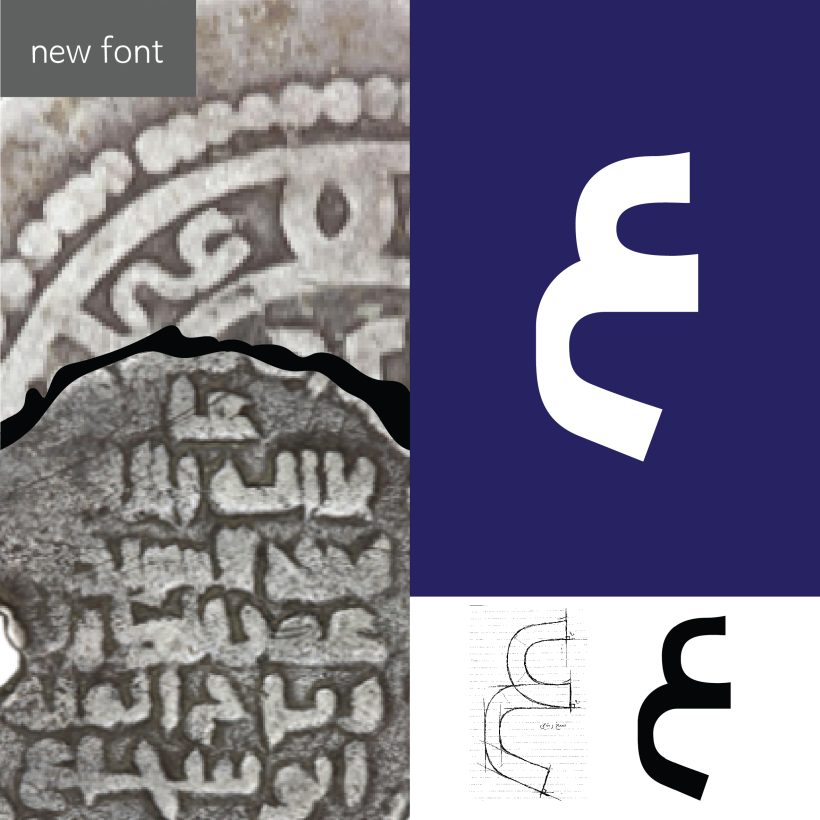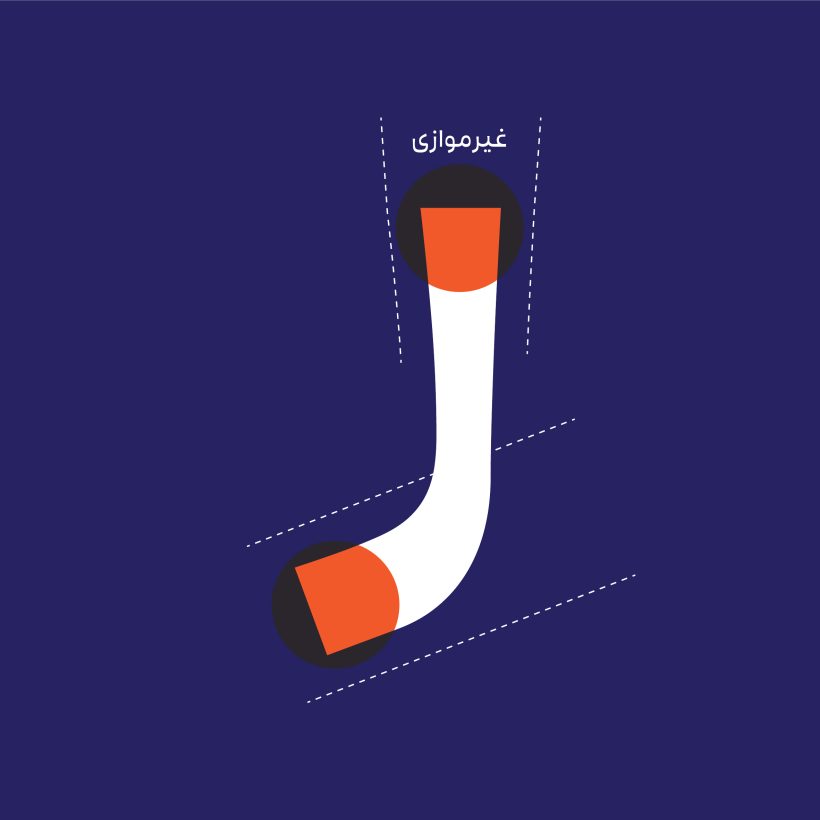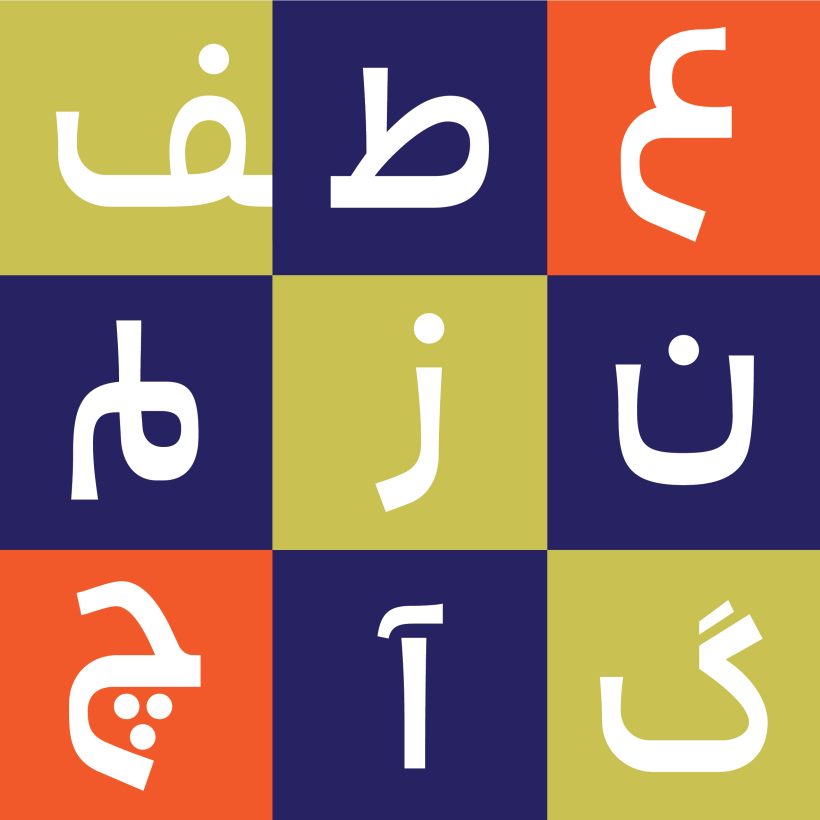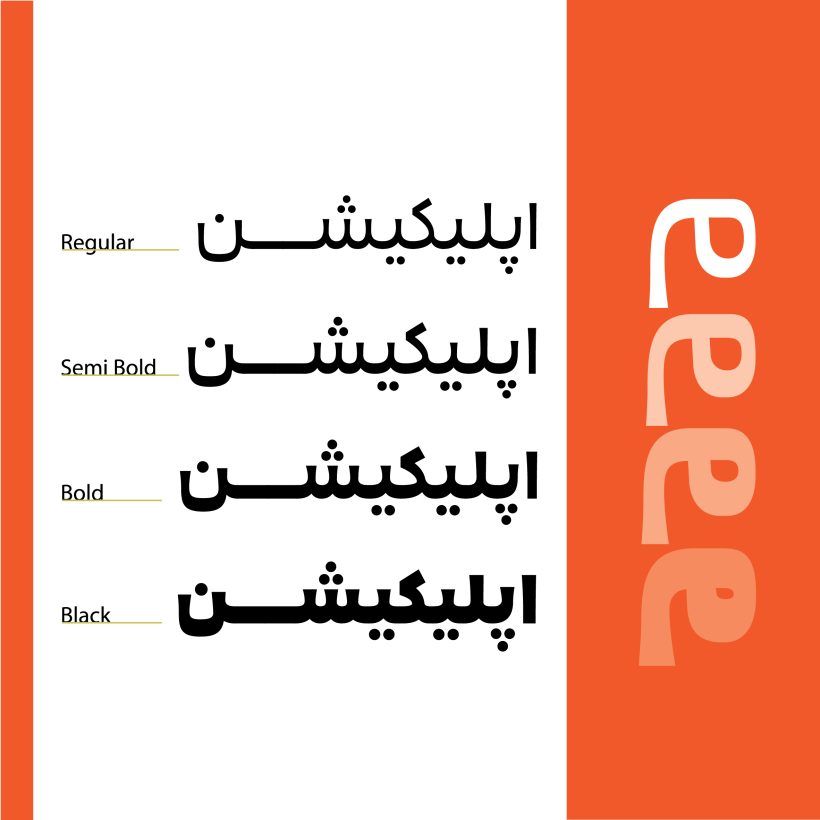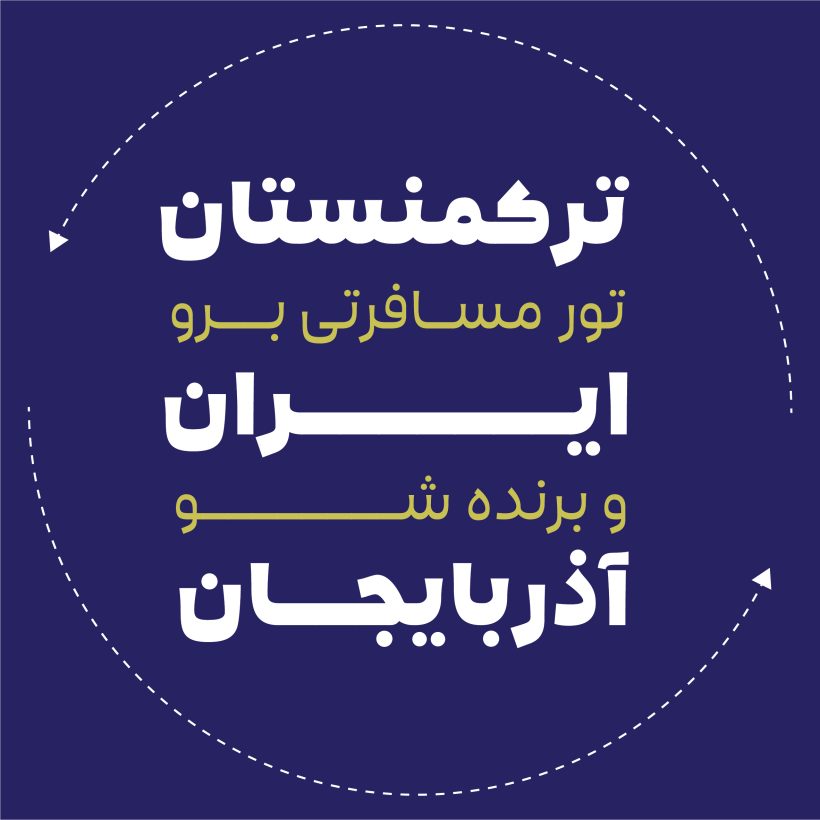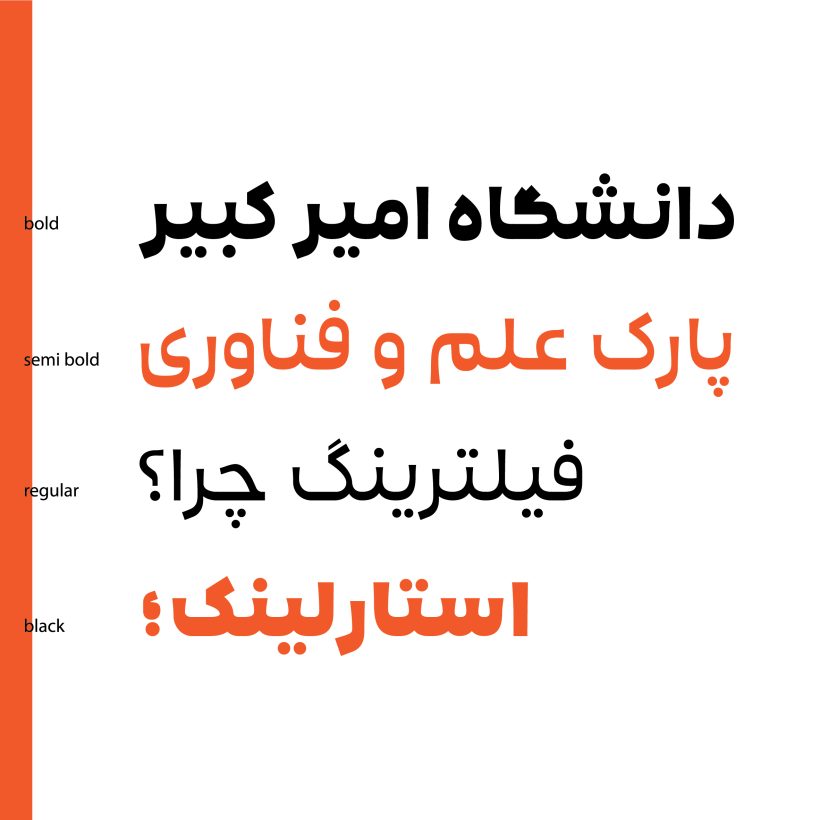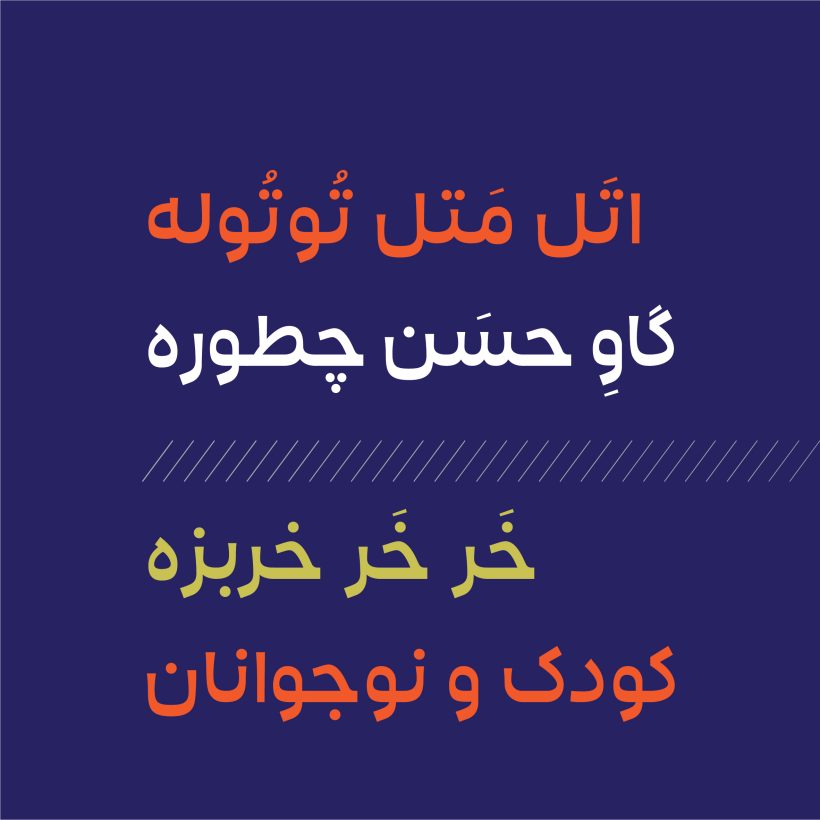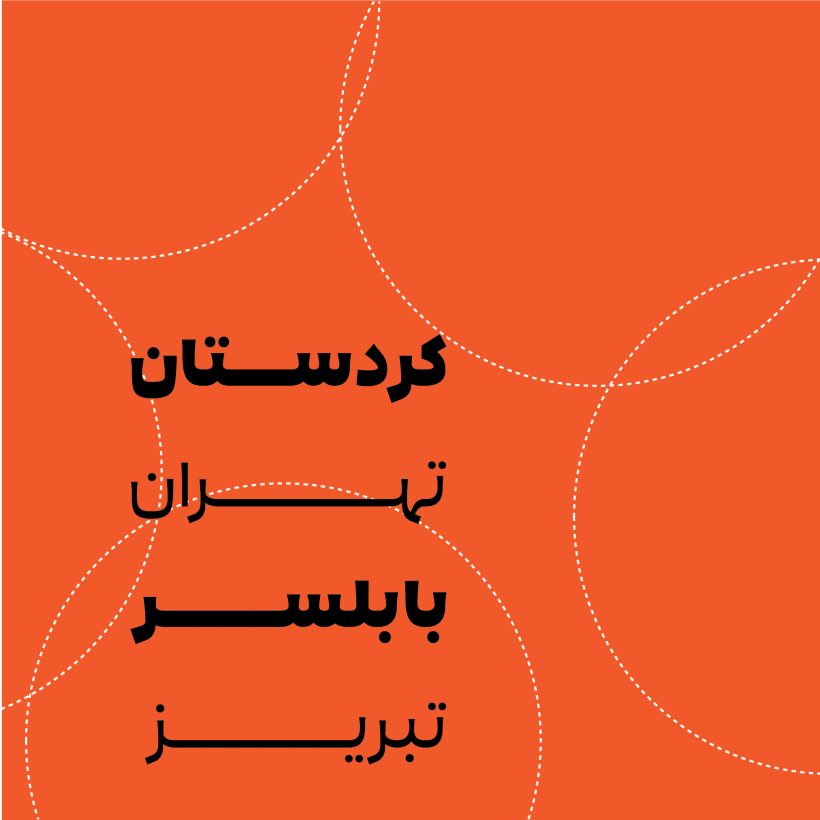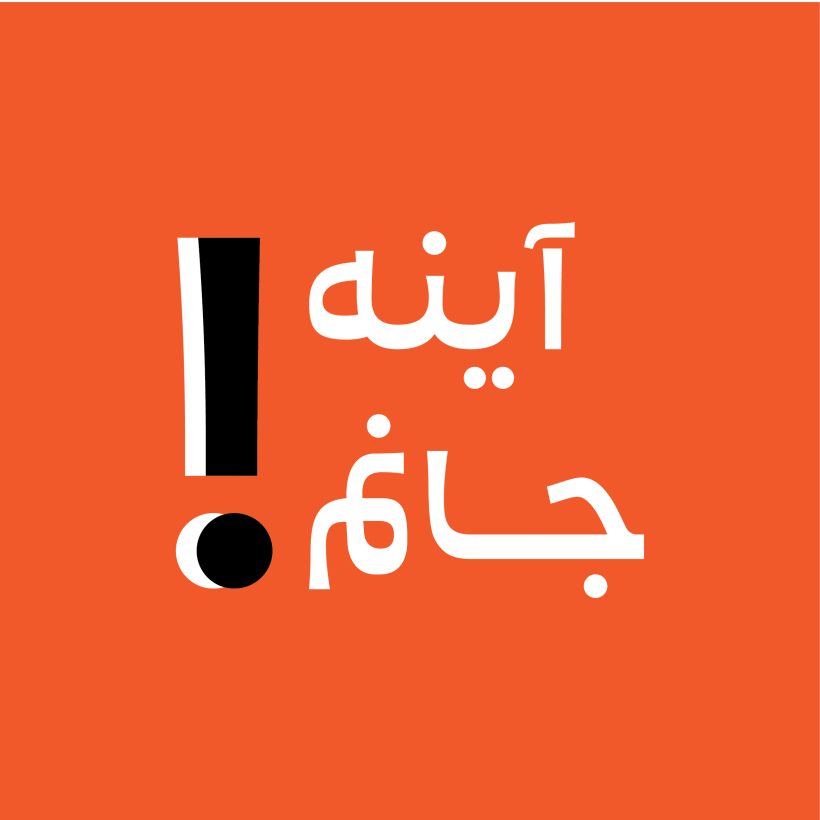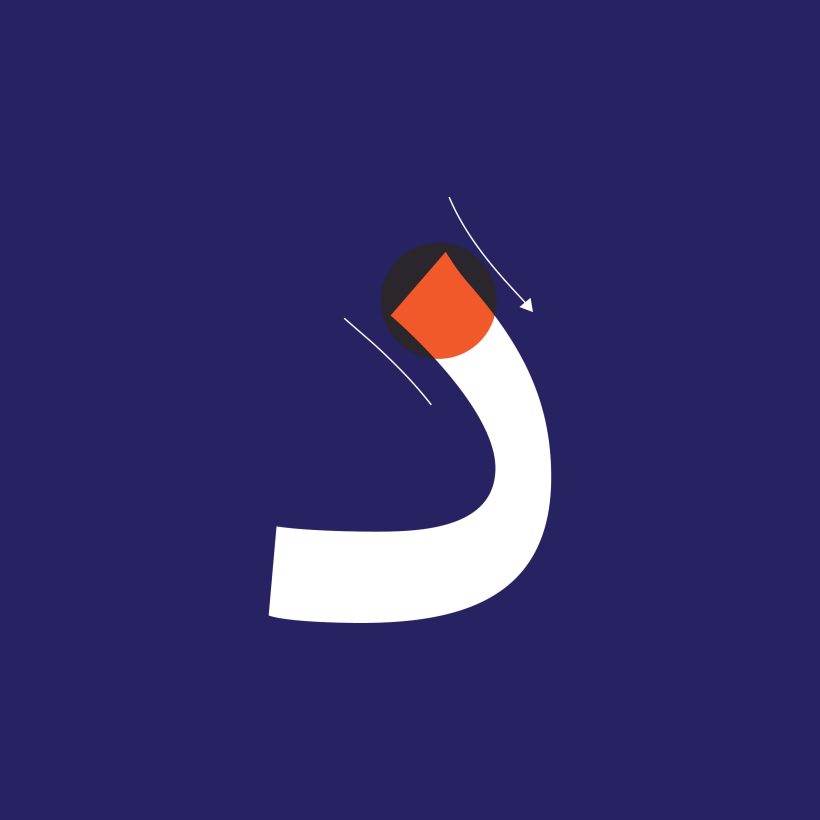
خانواده فونت هرما
فونت هرما با برداشتی نو از خطوط سکه های ضرب شده محفوظ در کتابخانه ملک طراحی شده است. هرما فونتی ساده، روان با لحنی صمیمی است و در چهار وزن طراحی شده است و برای متن، عبارت های مختلف و امور تبلیغاتی کاربرد دارد. استروک های فونت هرما از حرکات ساده هندسی شامل حرکات مورب و منحنی و حرکات عمودی غیرموازی تشکیل شده است. زاویه شروع و ختم حروف هرما برخلاف خوشنویسی سنتی به صورت افقی برش خورده است و دور حروف در فونت هرما بیشتر شده است. الفات فونت هرما تا حد ممکن همانندِ خط رقعی کوتاه قامتنـــد و حرف حلقوی با روزنه های درشت و بازتر طراحی شده است.
در ساختار فونت هرما از حالت مستقیم و یکنواخت حروف، کمی کاسته شده و شاکله حرکتی حروف، اندکی با حالت همراه شده است و با این ویژگی لحنی صمیمی تر دارد و از حالت رسمی آن کاسته شده است.
قواعد کرنینگ و اعراب گذاری ها در فونت هرما اعمال شده است. هرما دارای لیگیچر و کارکترهای جایگزین است تا برحسب نیاز و برای زیبایی بیشتر به کار گرفته شود.
فونت هرما توسط معصومه مصلح در سال 1401 طراحی شده است.
اعداد فارسی و عربی در فونت هرما تنظیم شده و قابل استفاده است.